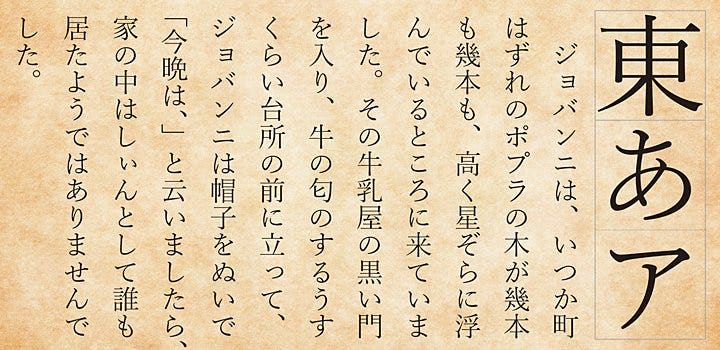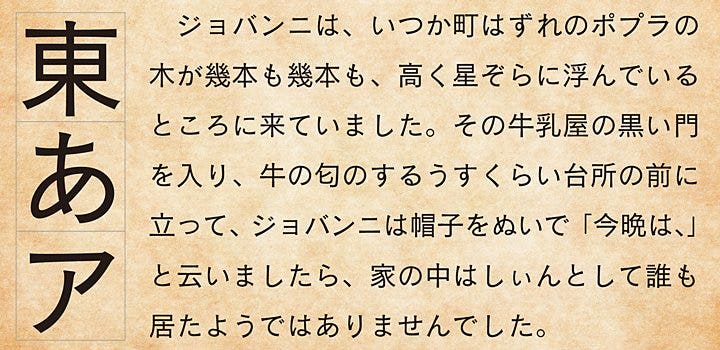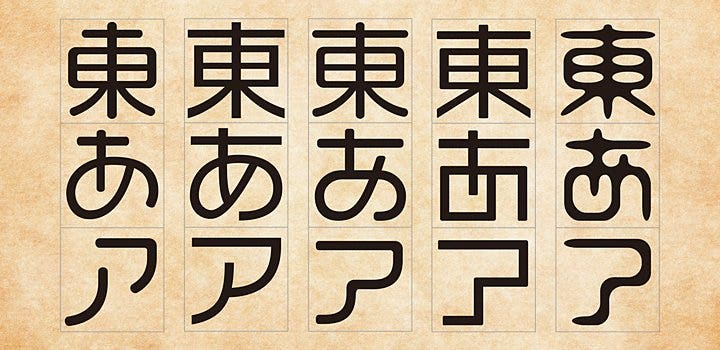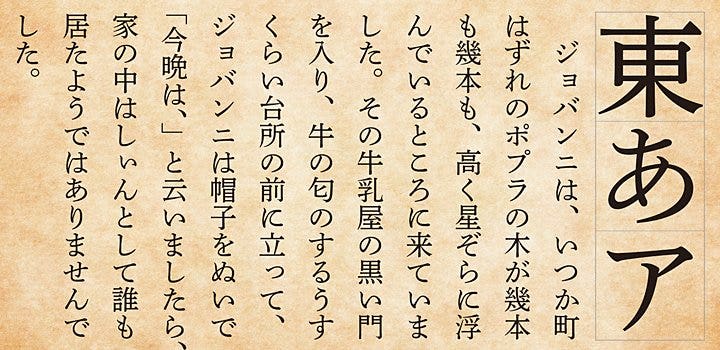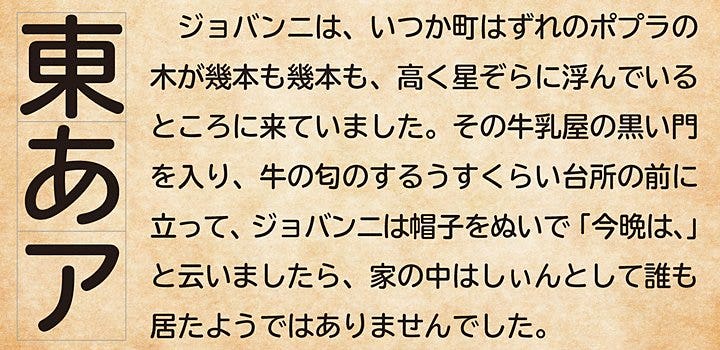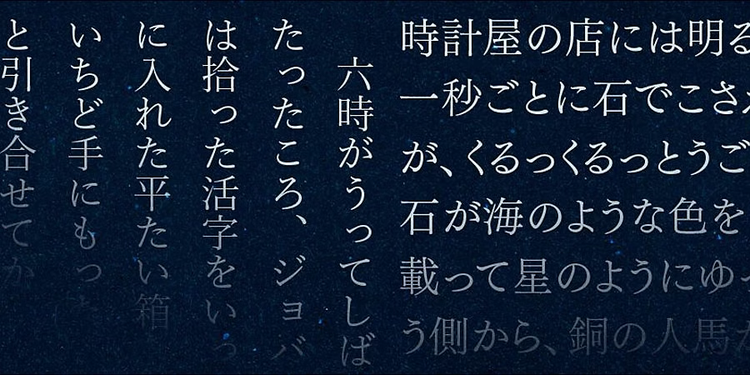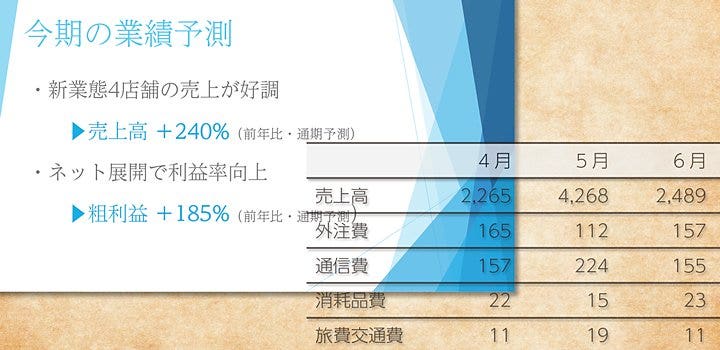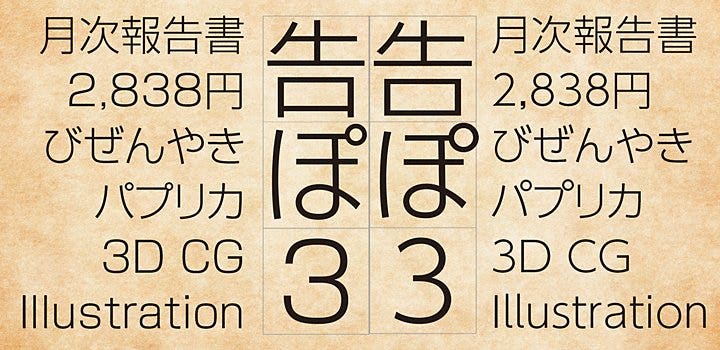
ビジネスシーンに最適なフォントの選び方
私たちはいま、パソコン上で非常に多くのフォントを使うことができますが、その多さゆえになんとなく目についたフォントや、好き・嫌いでフォントを選んではいないでしょうか?
文字のかたちも多くのバリエーションがあり、そのひとつひとつに書籍向け、新聞向け、
サイン・ディスプレイ向けというように、目的やデザインの意図が込められています。ここではビジネスシーンで使えるフォントについて基本的なフォントの分類を交えて紹介していきます。
ビジネス&プレゼンテーション向きなフォントとは
ビジネスでフォントが重要な役割を持つシーンとはどのような状況でしょうか。
すぐに思いつくシチュエーションは、資料やプレゼンテーション、対外的に発信するドキュメントを作るときでしょう。渾身の資料も、すぐれた内容のプレゼンテーションも、見にくい・読みにくい・わかりにくい……では伝わりません。
では、どうすれば見やすく、読みやすいドキュメントになるのでしょうか。
デザインにおいて、文字の見やすさと読みやすさの大部分は、フォントの選択+文字の配置(組み方=文字のサイズや文字間・行間の設定など)でコントロールすることができます。
つまり、より読みやすい、見やすいフォントを使うことは、伝わりやすさを追求するうえで大きな一助となるわけです。これはビジネスドキュメントだけでなく、あらゆる文字のデザイン・レイアウトも同様のことが言えます。
まずは手始めとして、フォントをビジネスドキュメントに活かすための第一歩として、まずは自分が持っている、使うことができるフォントをまず確認してみましょう。
フォントはパソコンにもともとインストールされているものもあれば、アプリケーションに付属しているもの、購入して使うもの、フリーフォントとして配布されているものなど入手方法もさまざま。知らない間に増えていたということもあるでしょう。
自分の環境にあるフォントが確認できたら、その中からビジネスドキュメント向きな書体を探っていきましょう。
明朝体は横線の太さに注意
明朝体は、横画が細く縦画が太い、漢字の横線の端や角にウロコと呼ばれる▲状のおさえがあるといった特徴を持った書体です。
用途や目的によりデザインも多様で、たとえば縦組みの雑誌や書籍本文向けに作られた書体は、かなが漢字に比べて小さく、縦長に設計されていますし、新聞向けに作られた書体はかなが大ぶりで平たく設計されています(上下比率を圧縮した文字を平体といいます)。
游明朝体
文字のかたちも、落ち着きのあるものから動きのあるもの、かっちりとした硬い印象のものから筆の動きを生かした柔らかいものまでさまざまで、その文字から受けるイメージを、表現したいコンセプトにうまく重ね合わせていくことで、伝えたいメッセージをより強く伝えることができるようになります。
では、プレゼンテーションやビジネスドキュメントで明朝体を使うときにはどのようなところに気をつければよいでしょうか。
そのひとつが横線の太さです。資料やスライドをプロジェクターなどで投影してみせる際には、環境によって細線が非常に見えにくくなることがあるからです。こうしたシチュエーションでは、横線を太くした「横太明朝体」や、可読性・可視性を重視したUDフォントを使うようにすると読みにくさを軽減することができます。
DNP 秀英横太明朝
なお、明朝体の特徴として、
同じかたち(骨格)で太さが異なるセット(ファミリーと呼びます)の中から、太いフォントを選んだとき、縦線は太くなっても横線はさほど変わらないことがあります。
このため、必ずしも太いフォントなら読みやすいとも言えないことに注意をしましょう。
ゴシック体・丸ゴシック体は細すぎ・太すぎに注意
ゴシック体は、横画・縦画が同じような太さで設計されており、ドキュメントやプロジェクターでも安定した読みやすさがあります。
セザンヌ
ゴシック体の先端を丸めた丸ゴシック体も、同様にビジネスの現場でも使いやすいフォントと言えるでしょう。
TBUD丸ゴシック
いずれも細いものから太いものまで幅広い太さを持つフォントファミリーで構成されているものも多く、使用するサイズに合わせて適切な太さを選ぶことで見やすい、読みやすいドキュメントを作ることができます。
一般的に大きい文字や大事なポイントには太いフォント、小さい文字には細いフォントを使用しますが、このとき注意したいのは、明朝体同様その線の太さです。
小さい文字だからと言ってあまりに細いフォントを使ってしまうと環境によっては非常に読みにくくなることがあり、逆に太すぎるフォントも文字の中の隙間がはっきり見えずに文字がつぶれてしまいます。画面やプリントでは十分に読めても、プロジェクター等でははっきり見えないことがあるということを念頭に文字の太さを決めましょう。
場合によっては、大きい文字にはあえて細めのフォント使うことで線の見にくさを大きさでカバーするという方法も有効です。
筆書体フォント・デザインフォントはワンポイントで
楷書体、行書体、草書体といった伝統的な書法によって書かれた文字のフォントや、明朝体、ゴシック体、丸ゴシック体等の分類に含まれない、いわゆるデザインフォントは、あまりビジネスシーンでは使われません。文章の見やすさ、見やすさよりも、目を引くこと、インパクトを出すこと、独特な表現を重視した文字のデザインが多いためです。
フォントが持つイメージをドキュメントに活かしたいという場合には、ワンポイントのキャッチや見出しだけに使うといった方法が有効です。
デザインフォント例:VDL メガ丸/ロゴナ/ロゴ丸Jr/ラインGアール/テラG
なかには分類上、デザインフォントに属しているものの、ビジネスシーンでも十分使えるゴシック体・丸ゴシック体風デザインフォントもあるので、使用する環境で見やすいかどうか、読みやすいかどうかを基準にフォントを選ぶとよいでしょう。
読みやすさ、見やすさにすぐれるUDフォント
これまでに紹介したフォント分類とは別に、判別しにくい文字をよりはっきりしたかたちにすることで、見間違えにくいこと、読み間違えにくいことを目指して作られたUDフォントというものもあります。
UD=ユニバーサルデザインとは、文化、言語、国籍、性別、障がいの有無、能力の差などを問わず、誰でも利用できることを目指した考え方です。
UDフォントは、視力が悪い人やその文字を見る環境によっては誤読しやすい文字でも、これまでのフォントよりも見やすい、読みやすい設計がされています。
たとえば、下図の例では、「口」の文字の下部の突き抜けをなくす、濁点、半濁点を大きくする、「3」と「8」を明確に見分けられるようにする、「C」「G」などの開口部を大きくするなどの処理が行われています。
左:新ゴ/右:UD新ゴ *新ゴはAdobe Fontsでは提供されていません
UDフォントは多くのフォントメーカーがリリースしており、種類もUD明朝体、UDゴシック体等さまざまです。該当フォントの多くは名前に「UD」がつけられており、一般のフォントと判別しやすくなっています。